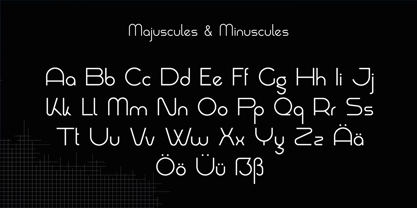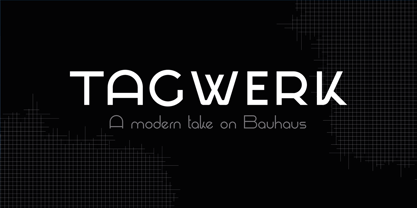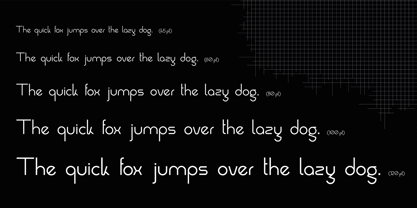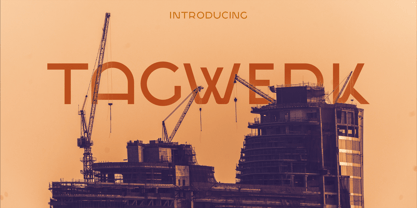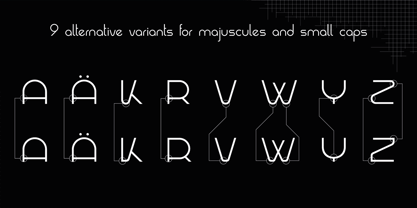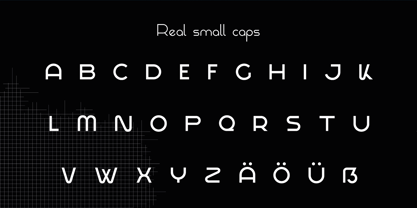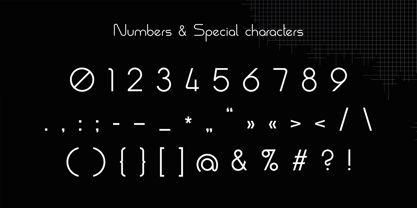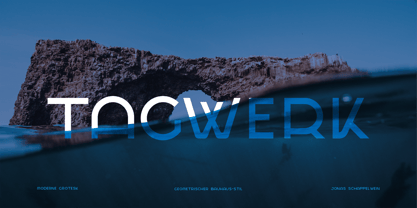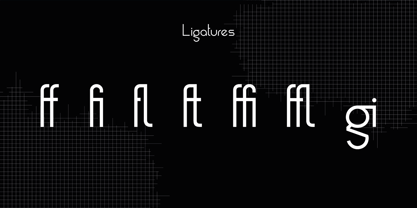
Tagwerk
The Tagwerk Font Family was designed by Jonas Schappelwein and published by Fontlabor. Tagwerk contains 1 styles. More about this family
»Tagwerk« hebt sich von anderen Schriften ihrer Kategorie durch den kreativen Einsatz von Extremen bei Ober- und Unterlängen und bei der Breite der Buchstaben. Der auffällige Kontrast zwischen Klein- und Großbuchstaben zeigt dies am deutlichsten: Die Großbuchstaben haben eine viermal größere Grundfläche als die Kleinbuchstaben.
Viele seiner Grundlagen sind von bekannten Bauhaus-Klassikern inspiriert. Sie wagt den Schritt über den Tellerrand hinaus und erweckt traditionelle, nostalgische Formen durch eine moderne, vom Bauhaus inspirierte Brille zu neuem Leben.
Das Ergebnis ist eine Schrift, die vor Rhythmus und Energie strotzt: eine dynamische Display-Schrift, die die alltäglichen Glyphen, die wir lesen und verwenden, in etwas Auffälliges, Zeitgemäßes und Charaktervolles umwandelt.